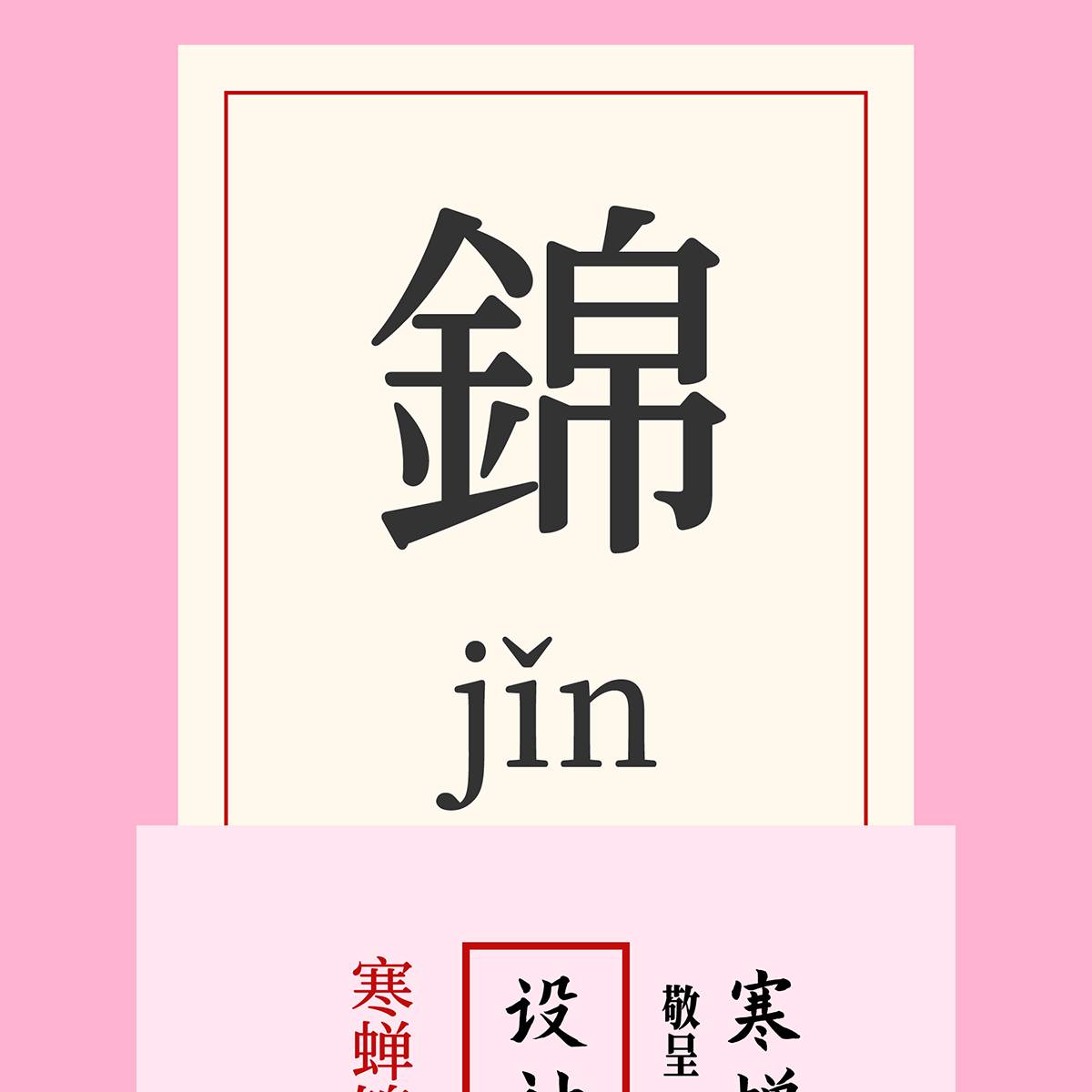
寒蝉锦书宋基于思源宋体添加圆角的一款免费字体
基于思源宋体(SourceHanSerif)修改,添加圆角,更加温润的宋体,排版细节优化,重构字重比例,字体粗细更加均衡,便于阅读。
名为锦书体,既是锦上添花,又是前程似锦之意。根据OFL协议,开源字体修改仍然开源,所以仍是开源字体,欢迎社会各界的朋友使用之。
关于宋体
宋体,是为适应印刷术而出现的一种汉字字体。笔画有粗细变化,而且一般是横细竖粗,末端有装饰部分。点、撇、捺、钩等笔画有尖端,属于衬线字体(serif),常用于书籍、杂志、报纸印刷的正文排版。源于宋朝,盛于明朝。国内普遍称为宋体,日本及其他地区称明朝体。所以在考虑是否在下一版本中将日文及传承字形名称更为“锦書明朝”。
宋体的设计老式宋体和现代宋体,和中规中矩的屏显宋体,老式宋体偏拙,屏显宋体均衡,现代宋体偏美术风格。中宫大小自不必说,中宫小的字体紧凑俊秀,中宫大的宋体排版整齐。均衡为最佳,这也是多数屏显宋体的选择。几年间,商用的宋体也出了不少精品,但可用于商用的字体确实聊聊无几,思源宋体、方正书宋、文鼎U明、一点明体,其他要么缺字,要么字形不符合使用规范,偏偏个人又更喜欢温润的宋体,觉得基础宋体的气质就应该是温润的,以至于对修改自思源宋体的“Shippori Mincho”爱不释手,一段时间,思源宋体基本没有使用过,思源宋体是有些现代风格的宋体,相比于其他屏显宋体笔画少了些细节。清晰锐利,简洁现代。优点是中宫适宜,骨架均衡,仍然是非常优秀的宋体。同时开源是非常好的范本。
在个人审美和力所能及的情况下修改了一版,重构了字重比例,添加圆角后更温润,添加窄体和宽体以及阅读显示用字,大字符集,三版本,确实要费不少功夫,原为自用,完成后发现确实不错,故分享出来。